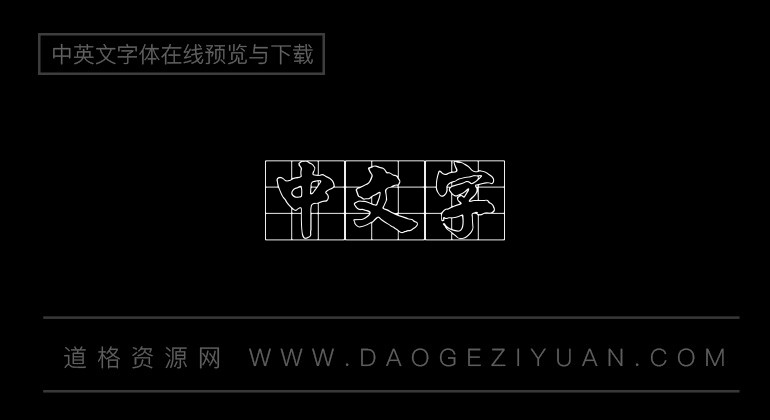
金梅碑楷九宮空心
金梅碑楷九宮空心字體是一款古典風格的楷書字體,它採用了九宮格的空心設計,使字體看起來更加精細和精緻。字體的筆劃細膩流暢,表現出古典文化的精髓,讓人彷彿置身於古代文化的氛圍中。金梅碑楷九宮空心字體適用於各種古典風格的設計,可以用於宣傳海報、書籍封面、廣告等設計之中。
金梅碑楷九宮空心是一款非常不錯的手寫藝術字體,具有很好的視覺感,適合於文化類的宣傳設計、商業類品牌的廣告和產品包裝設計以及個性化文字排版等較多場景。